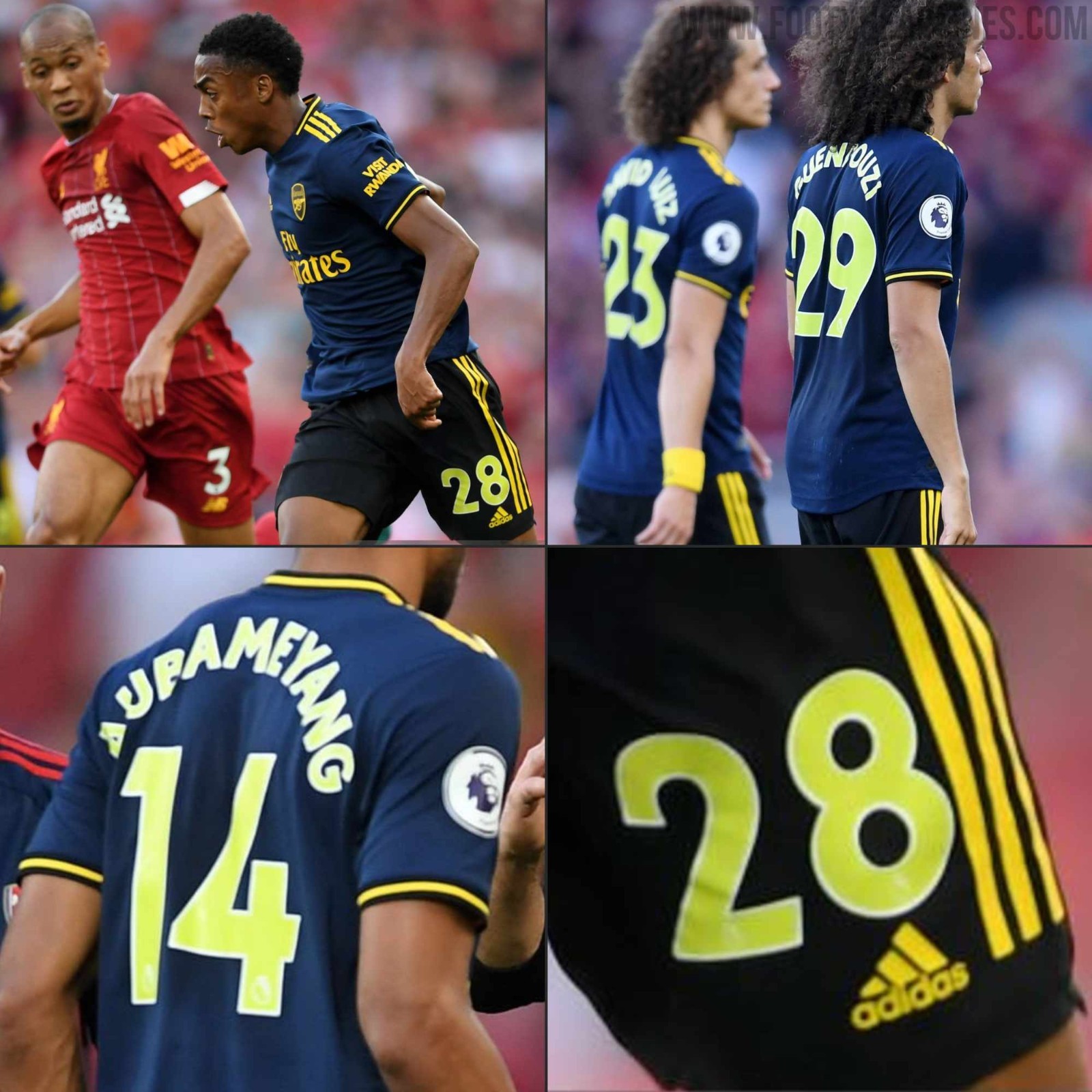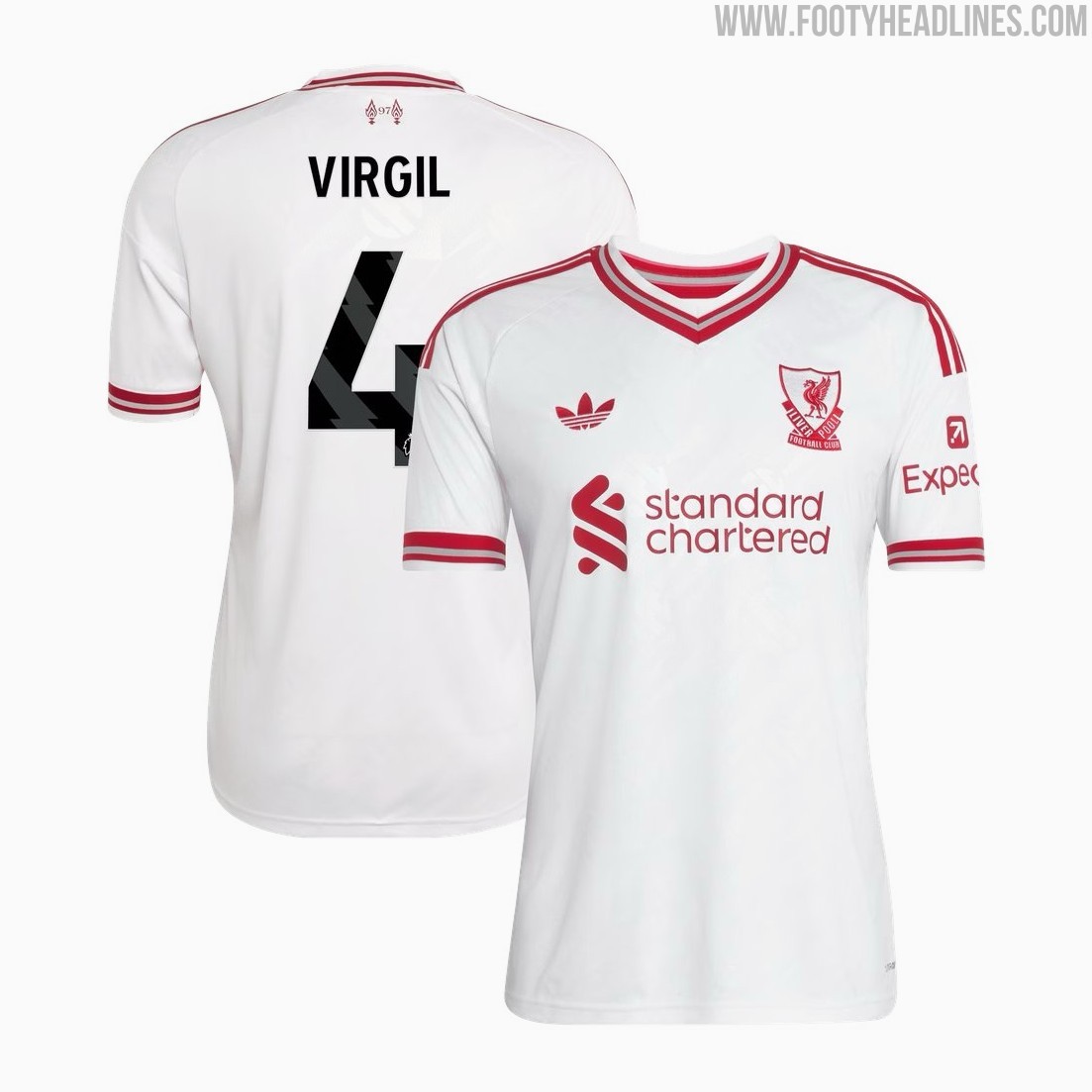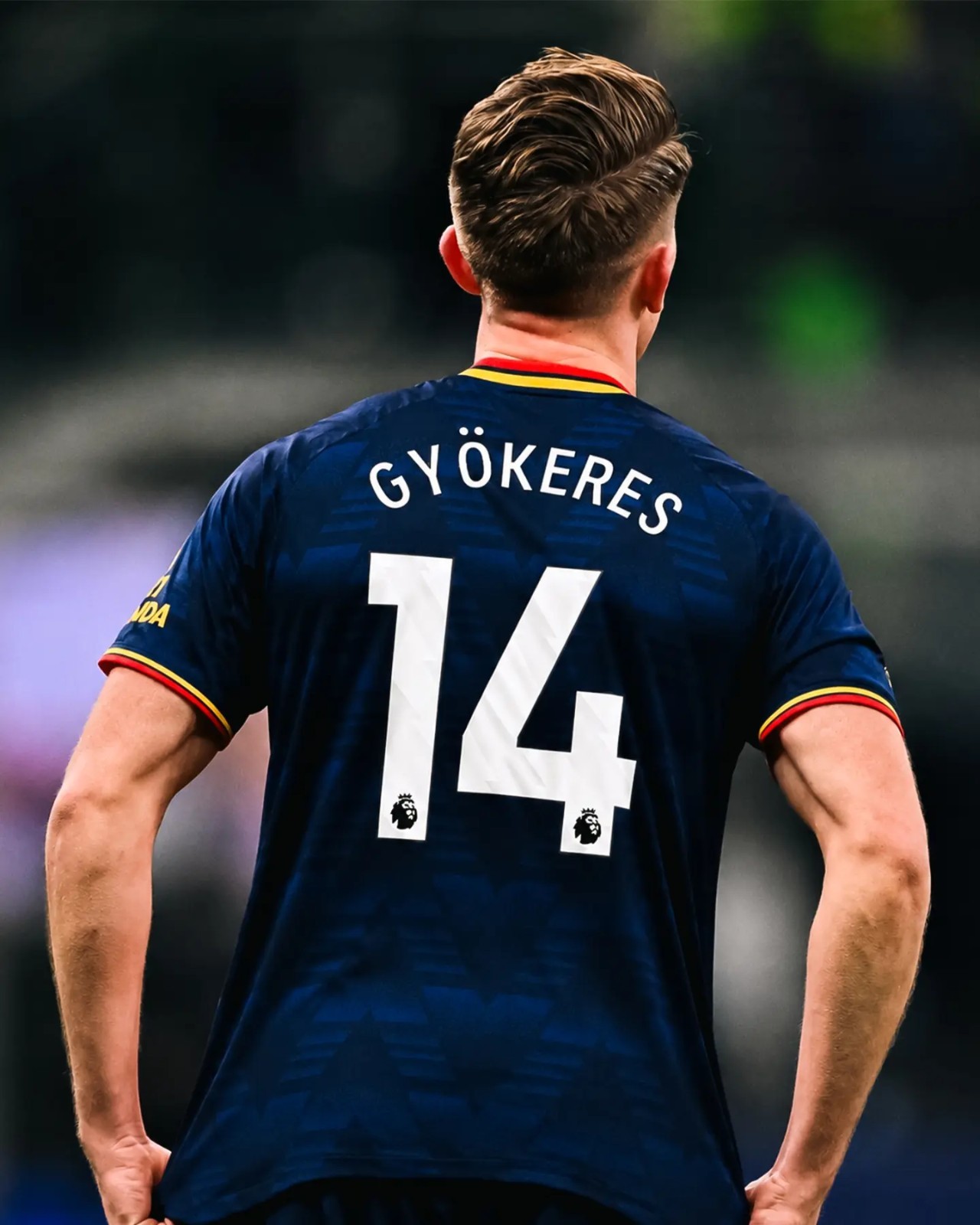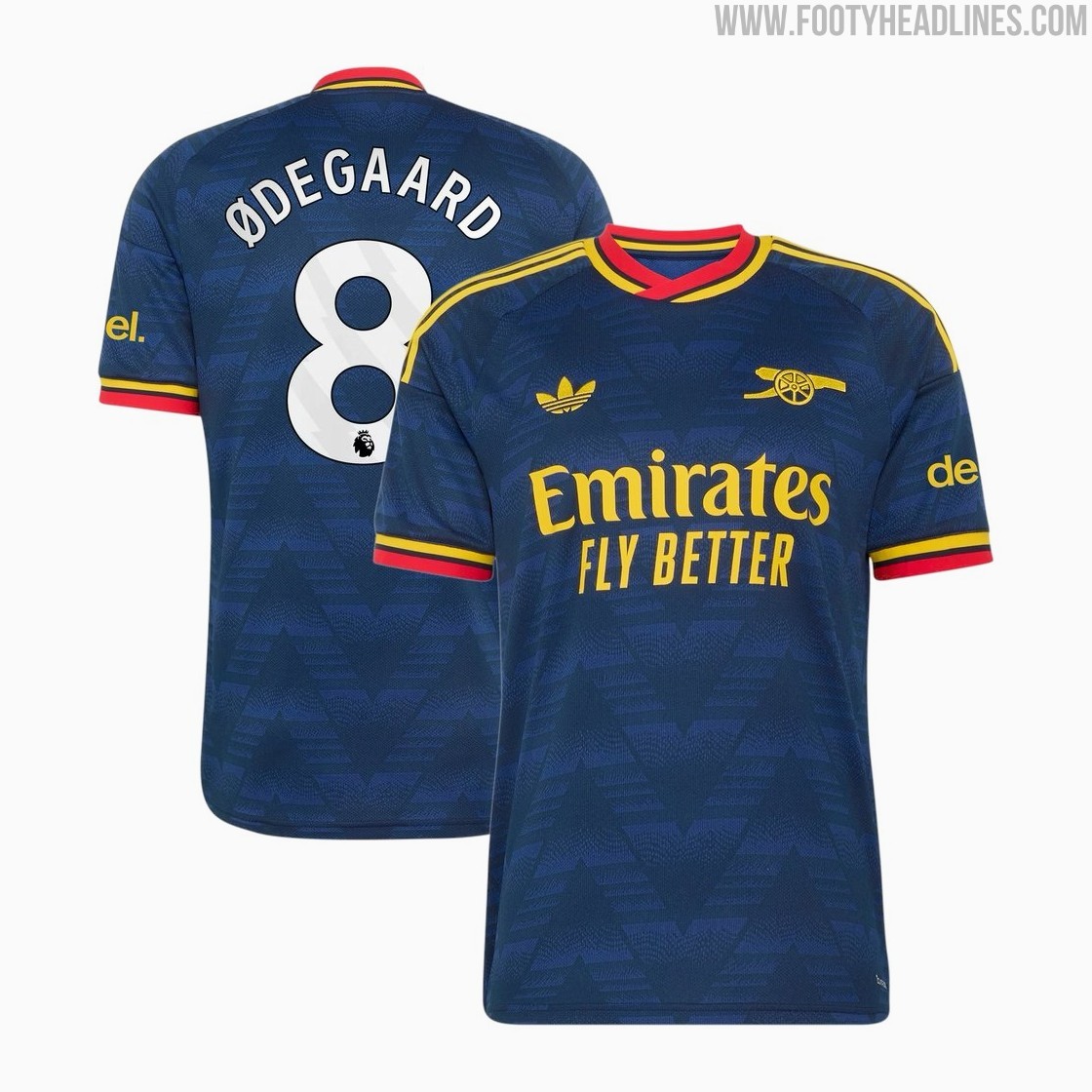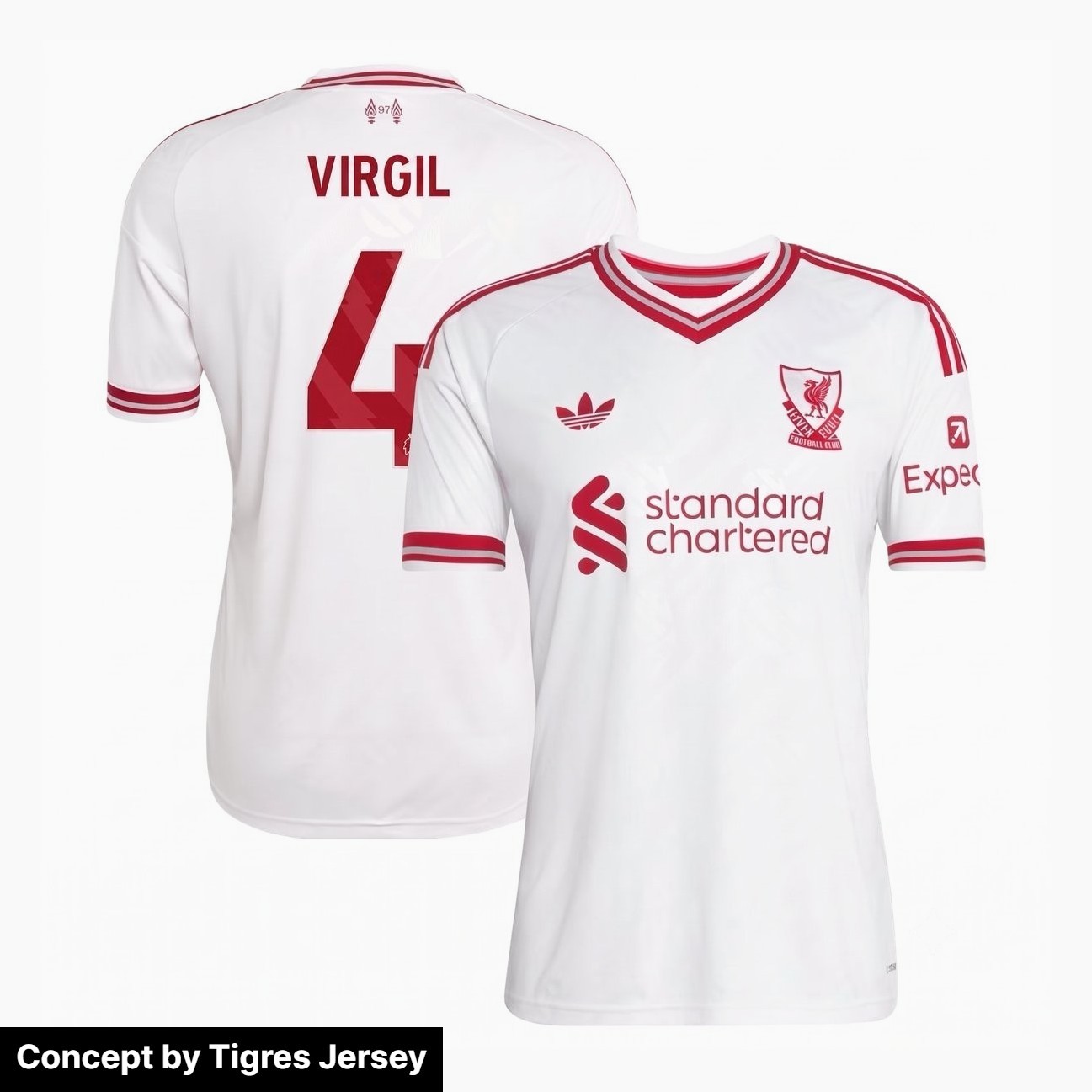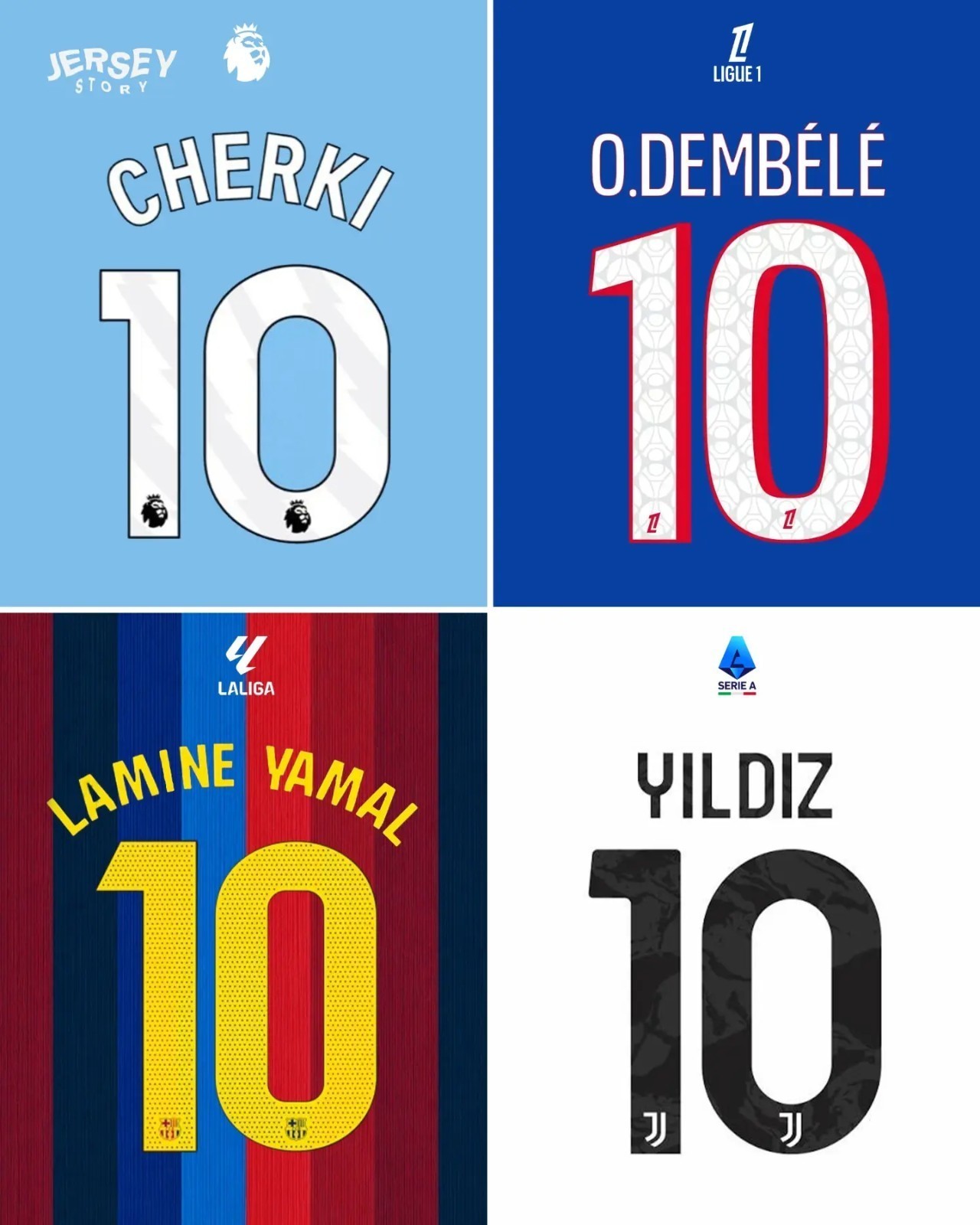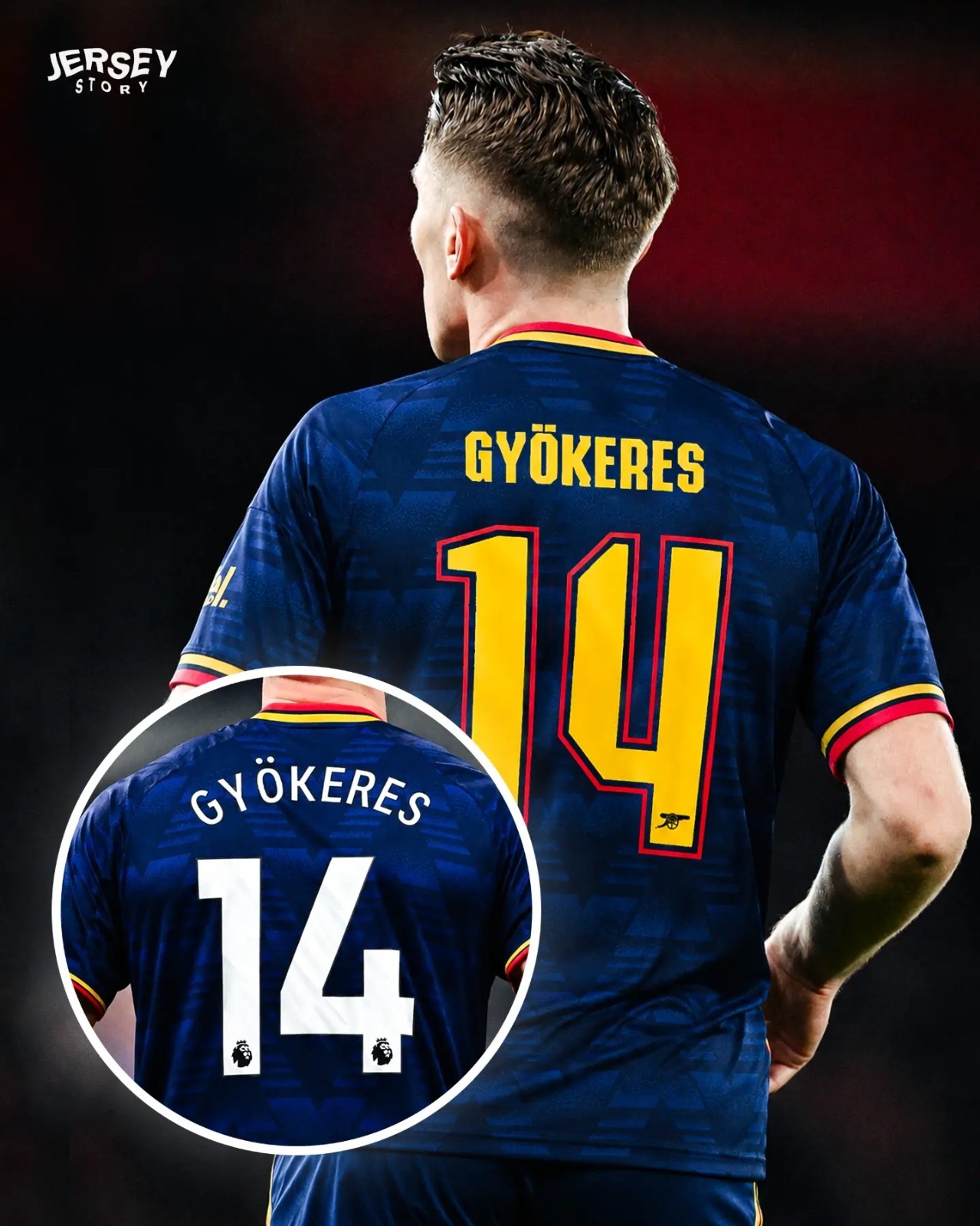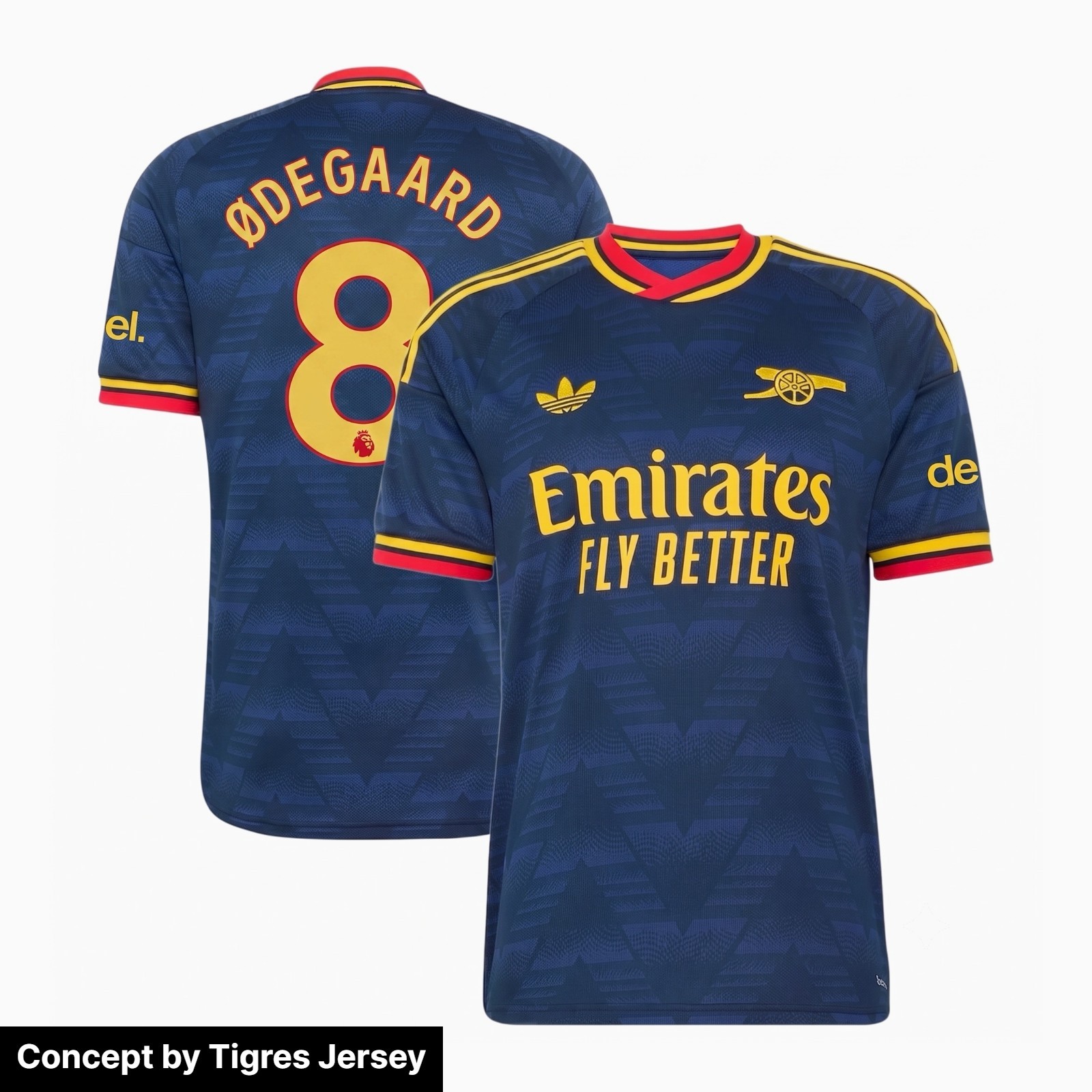
La Premier League tiene que arreglar la rigidez de la tipografía de sus camisetas
• Rigidez de la Tipografía de la Premier League: La Premier League es la liga más restrictiva en cuanto a la tipografía de las camisetas, permitiendo solo cinco combinaciones de colores estándar (blanco, negro, rojo, azul marino y amarillo de alta visibilidad) para todos los clubes.
• Desajuste de Colores en las Camisetas: La restricción de solo cinco opciones de color para la tipografía provoca que los nombres y números no combinen armoniosamente con los diseños personalizados y los colores específicos de las camisetas creadas por los fabricantes.
• Flexibilidad en Otras Ligas: Ligas como la Serie A, La Liga y la MLS permiten a los clubes personalizar los colores de la tipografía para que coincidan con los diseños de sus camisetas, un enfoque que la Premier League podría seguir para mejorar la estética.
Aunque las tipografías estandarizadas de las ligas se han convertido en algo habitual en el fútbol europeo, la Premier League sigue siendo, con diferencia, la más restrictiva en cuanto a la ejecución visual. Incluso después de introducir una tipografía renovada hace unos años, la liga sigue imponiendo un límite estricto de solo cinco combinaciones de colores autorizadas para los 20 clubes: blanco, negro, rojo, azul marino y amarillo de alta visibilidad.
La Premier League tiene que arreglar la rigidez de la tipografía de sus camisetas
Maqueta de Jersey Story
Colores que no combinan en la Premier League por tener solo 5 opciones de color
El problema con el reglamento de la Premier League es que choca con el diseño de las camisetas. Los fabricantes de equipaciones crean camisetas a medida con colores de contraste específicos, como el dorado, el granate, el crema, el menta o incluso un simple amarillo. Sin embargo, cuando esas camisetas se llevan en los partidos de la máxima categoría inglesa, los equipos se ven obligados a elegir entre las cinco opciones de color predeterminadas.
Un ejemplo claro lo vemos en la camiseta visitante del Arsenal de la temporada 26-27, donde el nombre personalizado a juego que se usa en las competiciones de copa combina a la perfección con los detalles de la camiseta, mientras que la alternativa obligatoria de la Premier League desentona visualmente con el diseño de la camiseta. En la temporada 26-27, el Arsenal decidió usar nombres y números blancos, después de que en la 19-20 eligieran la opción en amarillo de alta visibilidad, que desentonaba con el amarillo de la camiseta.
Del mismo modo, el Liverpool eligió el negro para su camiseta visitante de la Premier League de la temporada 26-27, simplemente porque el rojo de la EPL es de un tono más llamativo que el rojo que usa Adidas.
Los expertos mexicanos en camisetas de Tigres Jersey han creado dos bocetos de cómo quedaría una tipografía de la Premier League a juego con estas camisetas.
Es hora de seguir el ejemplo de otras ligas
Otras competiciones de primer nivel ya han demostrado que la coherencia de marca y la armonía de las camisetas pueden coexistir fácilmente. Ligas como la Serie A, La Liga y la MLS exigen una única tipografía oficial para facilitar la legibilidad, pero dan a los clubes total libertad para personalizar los colores de la tipografía y que combinen con los detalles específicos de cada camiseta. Por su parte, la Bundesliga ofrece total libertad creativa al permitir tipografías a medida para cada camiseta.
Con solo relajar un poco las restricciones de color y mantener su tipografía oficial, la Premier League podría resolver al instante los desajustes de color y mejorar el diseño de las camisetas en toda la liga.